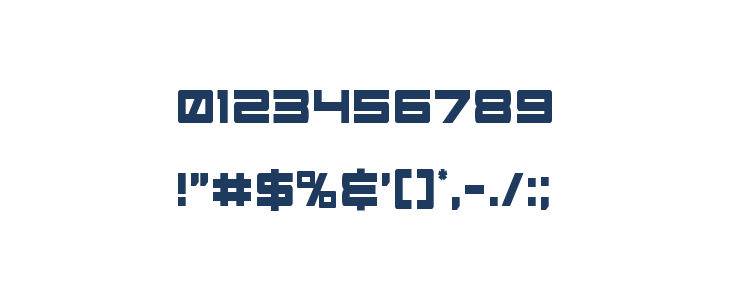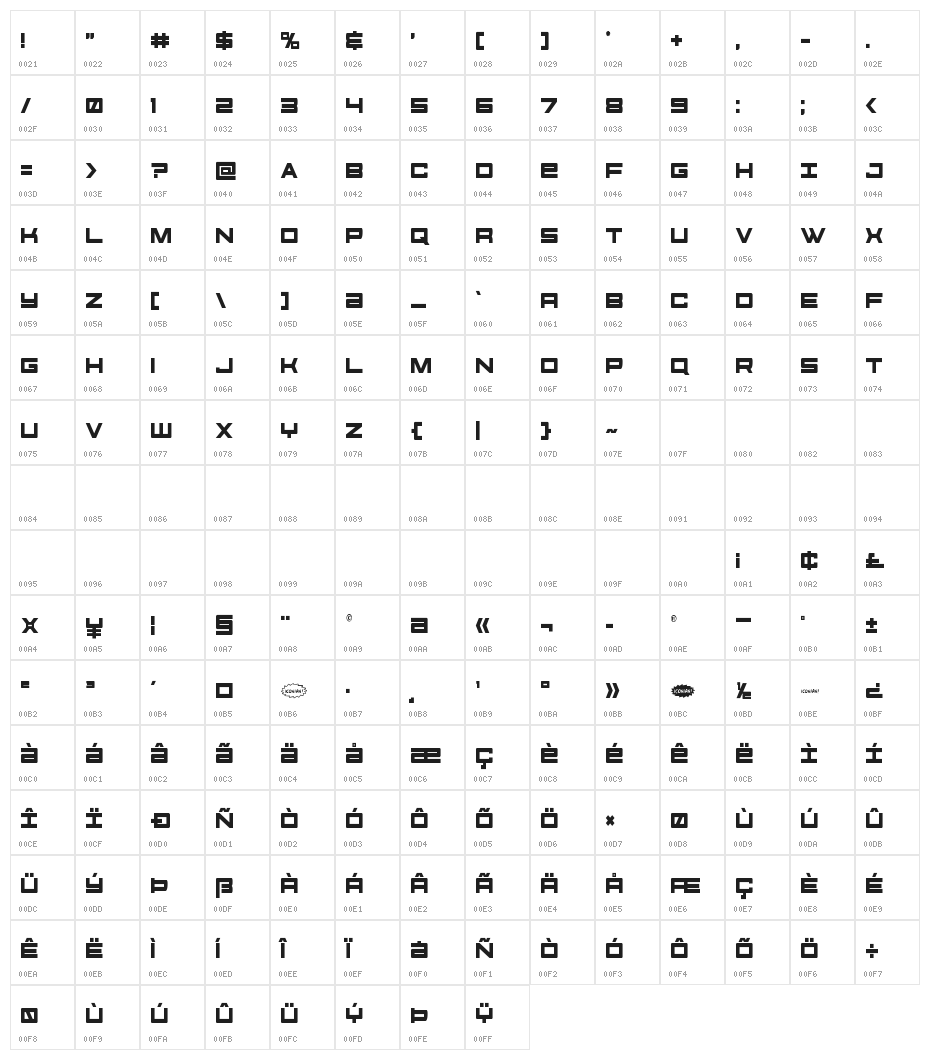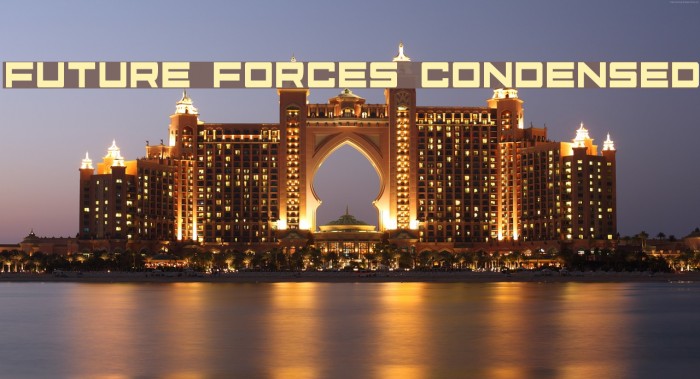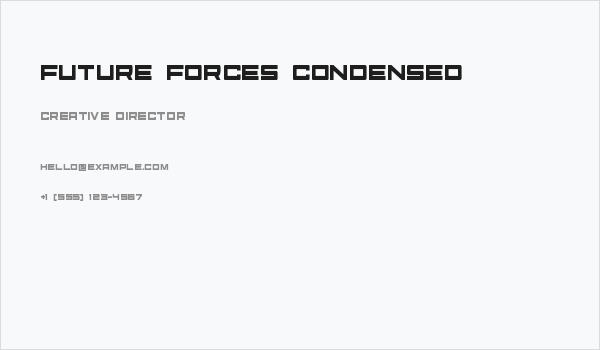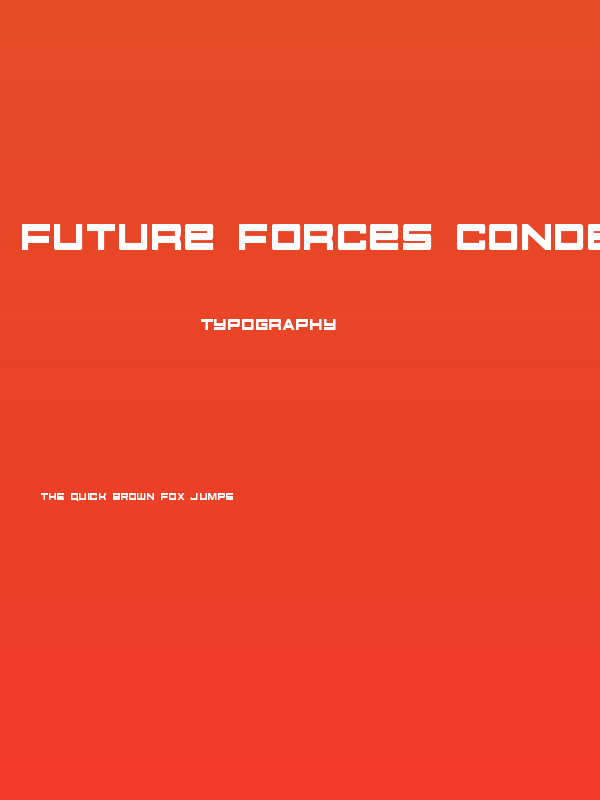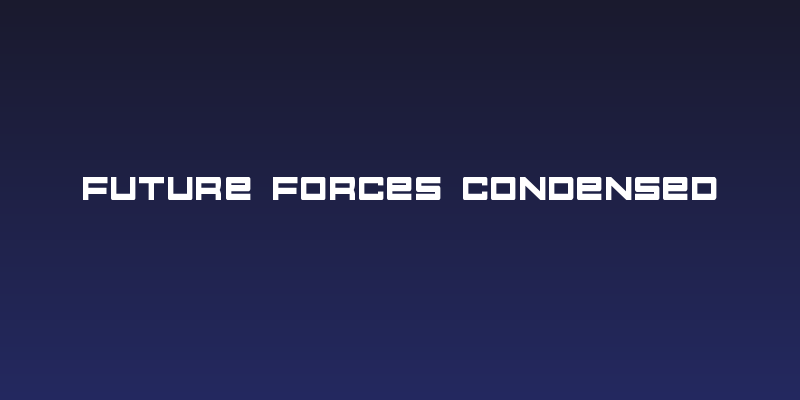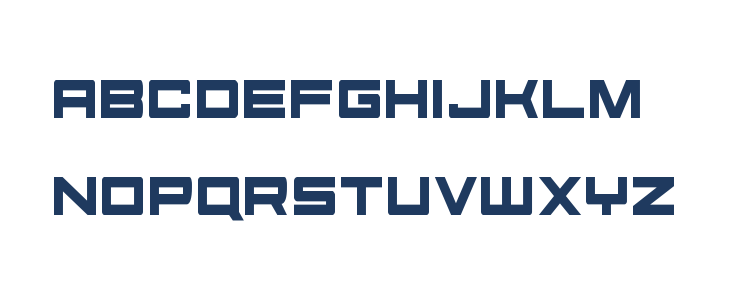
Future Forces Condensed Font
| Vorgeschlagene Projekte | Ideal for sci-fi themed designs, technology branding, video game interfaces, and modern posters. |